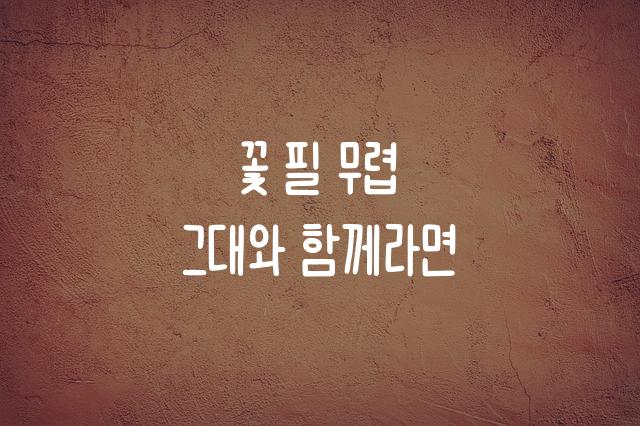
낼나 리지체
낼나 리지체는 아이들의 순수하고 귀여운 손글씨에서 영감을 받은 폰트로, 또박또박한 글자 형태가 특징입니다. 이 폰트는 따뜻하고 친근한 느낌을 전달하며, 어느 곳에나 부드럽게 어우러집니다.
이 폰트의 인사이트!
통통 튀고 장난기 가득한 어린이의 목소리 같은 스타일로, 독자에게 친근하고 따뜻한 느낌을 줍니다.
낼나 리지체은(는) 손글씨, 귀여운 스타일, 레트로, 감성적인 계열의 생김새를 가지고 있으며
로고 디자인, 포스터, 광고 캠페인 등에서 자주 활용되며, 효과적인 메시지 전달에 적합합니다.
이 폰트는 크리에이티브, 엔터테인먼트, 이벤트/웨딩 분야에 잘 어울리며,
창의적인, 강렬한, 재미있는 느낌을 담고 있는 것이 특징입니다.